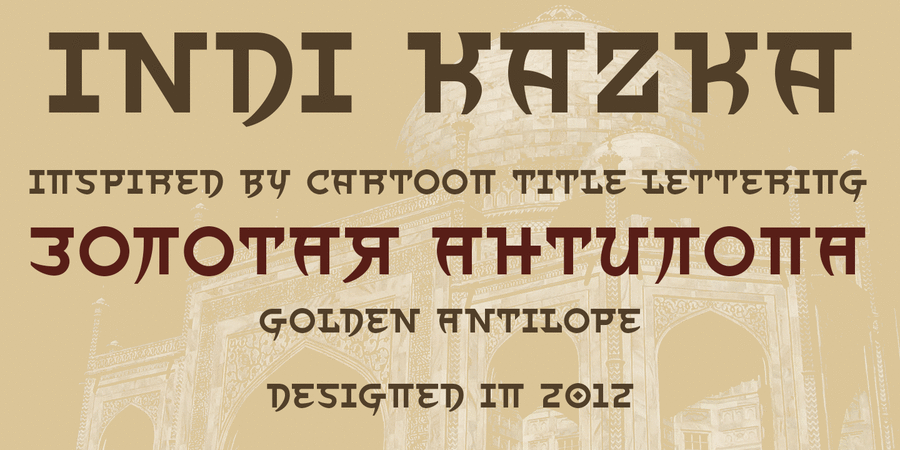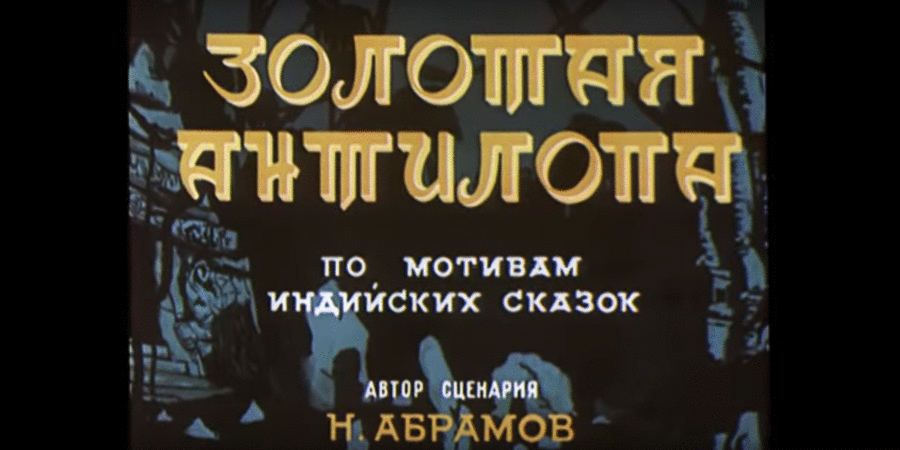
Indi Kazka – акцидентний геометричний гротеск, стилізований під деванагарі. Шрифт створювався під враженням від літерації з мультфільму «Золота Антилопа» (1954) за мотивами індійських казок.
Шрифт розроблений Сергієм Ткаченком у 2012-2018 році.